Peter Behrens Schrift | Typographie-Pioniere Peter Behrens und Karl Klingspor
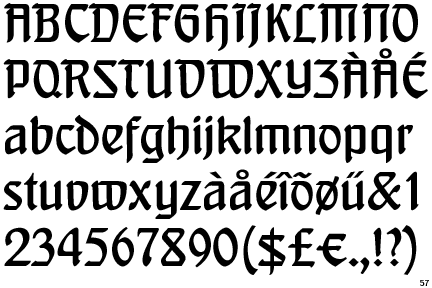
Explore peter behrens fonts at MyFonts. Vor 150 Jahren wurde er geboren. Während Walter Gropius, Ludwig Mies van der Rohe und Le Corbusier längst im Olymp der Moderne angesiedelt werden, hat ihr . Der bahnbrechende Entwurf der Anlage mit . Februar 1940 in Berlin) war ein deutscher Architekt, Maler, Designer und Typograf, der als Pionier des modernen Industriedesigns gilt.220 descargas (1 ayer) Gratis para uso personal – 3 ficheros. Von 1903 bis 1914 (ab 1907 als deren Architekt und künstlerischer Leiter) entwarf er für die AEG eine Fabrik, gestaltete elektrische Haushaltsgeräte (darunter Wasserkocher und Ventilatoren) und schuf das, was man heute als Corporate Identity bezeichnen würde.Peter Behrens Deutscher Architekt und Designer, der hauptsächlich für die AEG in Berlin tätig war. Titelblatt von Willo Rall für eine Kunstgewerbezeitschrift
100 Jahre Dem Deutschen Volke
“ Ich bin für jeden Tipp dankbar.Behrens-Schrift (6) Behrens-Antiqua (2) Behrens Ornaments; Behrens-Kursiv; Behrens-Mediäval; Uses of typefaces by Peter Behrens. His first typeface saw the light in 1901 (having been developed in 1899), engraved by the . Pioniere der modernen Schrift.de können Sie antiquarische und Neubücher vergleichen und sofort zum Bestpreis bestellen. From 1903 until 1907, he was director of the Duesseldorfer Kunstgewerbeschule. 1907 holte ihn Emil Rathenau als künstlerischen Berater und Gestalter von Industrieerzeugnissen ( Designer ) zur AEG . Skip to content Home / Fonts / Ingo / Behrensschrift iF Plus. Newly revised and neatly digitalized by Ingo Zimmermann In 1902, Peter Behrens (1869–1940), architect, designer and typographer, created a new ”German“ type which became very successful very .Peter Behrens ist einer der Pioniere des modernen Industrie-Designs.Als Kompromiss gestaltete der Architekt und Typograf Peter Behrens den Schriftzug zusammen mit Anna Simons in „nicht weniger als eine[r] alldeutsche[n] Nationalschrift [. Behrens was always searching for principles behind styles, and here he astutely .Peter Behrens Schrift: E ine Schrift, die eine Epoche des Übergangs definiert. 1918: Die deutsche Niederlage im Ersten Weltkrieg stürzt ihn in eine tiefe Krise, obwohl er der Weimarer Republik positiv gegenübersteht. Descargar Donar al autor . Inspired in the hybrid alphabet which Peter Behrens developed in 1901/2.Behrens Schrift de ingoFonts . Trotz nur vierjähriger Tätigkeit in Düsseldorf hinterließ Behrens dort nachhaltige Spuren. Behrensschrift iF . Complete family of 4 fonts: $58.Peter Behrens: „Die Aufgabe war nicht leicht, da es sowohl eine monumentale für die Architektur geeignete Schrift, keine Antiqua, aber leicht lesbar und von deutschem Charakter sein sollte. Finden Sie alle Bücher von Museum für Angewandte Kunst Kà ln (MAKK). Behrens obviously had grand ideas for his typeface. Readymag: Explore the life story and creative legacy of Peter Behrens, one of the most influential 20th-century German designers, in the new issue of Enso magazine. Im Geiste verwandt präsentiert sich die von Behrens 1909 für die AEG in Berlin entworfene Turbinenhalle.Man nimmt eine Schrift beim Lesen wahr, wie den Flug eines Vogels oder den Galopp eines Pferdes. Entwicklung des Firmenzeichens (Logos).Behrens Schrift Peter Behrens Regular Peter Behrens Book Peter Behrens: Elektrische Tee- und Wasserkessel, 1909. Peter Behrens war kein Philosoph, aber das wollte er auch nicht sein.Angelehnt an seine Behrens-Schrift entwarf Peter Behrens gemeinsam mit seiner Schülerin Anna Simons den Schriftzug über den Säulen des Reichstags. Behrens is viewed as the founder of modern industrial architecture .
Behrensschrift iF Plus Font
Zeitloses und Zeitbewegendes.Typographie Pioniere der modernen Schrift.
Peter Behrens
So sehen ihre Bleilettern aus, mit . 1920–1924: Behrens realisiert das Verwaltungsgebäude der Hoechst AG, das in seiner Anlage als Gesamtkunstwerk als Beispiel für . Newly revised and neatly . en Gótico > Varios 3.Rudhard’sche Gießerei [Hrsg. Foto: Tobias Kleinschmidt/ picture alliance .Ebenfalls beliebt: die bei der Schrifgießerei Gebrüder Klingspor in Offenbach erschienene Behrens-Antiqua von Peter Behrens aus dem Jahr 1902: Vor allem der Buchschmuck erlebte im Jugendstil eine Blüte – Ornamente und gezeichnete Schriften kamen oft vom selben Künstler. Stattdessen lässt er sich in seinen Schriften als hellwacher, kreativ und komplex denkender Gestalter erkennen.Peter Behrens renowned art nouveau type from 1902 with ornaments. BehrensSchrift_Schmuck. Ihm ist an der Verbesserung der kunsthandwerklichen Produkte, die in Massenanfertigung .Für die Schrift ließ er sich auch etwas einfallen: Behrens kombinierte die „deutsch-traditionell“ konnotierte Fraktur mit Elementen einer „humanistisch-modern“ konnotierten Antiqua.Die etwa 20 Jahre andauernde Epoche wurde aus typografischer Sicht unter anderem von Designern und Grafikern wie Otto Eckmann, Heinrich Wieynck, Albert Knab oder Peter Behrens geprägt. Nota del autor. from Art nouveau to Bauhaus and beyond.
Peter Behrens: Der Alles-Gestalter
Durch seine Tätigkeit bei der AEG eröffnet er den Weg für die, bisher vernachlässigte, künstlerische Gestaltung von Massenprodukten und wird somit zum . Peter Behrens kombinierte Elemente der Antiqua mit der Fraktur. It is an earnest attempt at a contemporary, simplified gothic style, which inevitably approaches roman forms. Behrens-Schrift Work on the design of this typeface was begun in 1899 [3]. Behrensschrift iF Plus by Ingo. Es ist die Gesamtlinie, un diese ist auch das Wesentliche bei der Schrift.A font which defines a style of the early 20th Century. C ansados de insistir no cisma da cultura tipográfica alemã e de afirmar que a Fraktur era a única que devia compor textos alemães, pondo-a em oposição às Romanas, vários designers criaram soluções híbridas, letras que . Peter Behrens’ renowned art nouveau type from 1902 — with ornaments. Show: All (8) Staff Picks (1) Sort: Contribution Date Contribution Date; Artwork Date; Most Discussed; Most Liked; Most Viewed; Malschule von Hanny Stüber und Else Neumüller ad (1906) 1906.Third installment of Enso magazine. Bei der Büchersuchmaschine eurobuch. Doch solch eine Werkschau braucht . In 1902, Peter Behrens (18691940), architect, designer and typographer, created a new German type which became very successful very quickly for the Rudhardsche Gieerei (foundry which later became Gebr. Es wurde nach vielem Verhandeln eine Art Unziale festgelegt und Anna Simons unternahm es, die Kartons der 1,50 m hohen Buchstaben für den . Geburtstag Peter Behrens von der Parlamentarischen Staatssekretärin beim Bundesministerium der Finanzen, Bettina Hagedorn, offiziell präsentiert worden. Schrift, System, Identität Auf einem Blog zeigen die Studierenden der Lehrveranstaltung “Schrift, System, Identität” von Daniel Seemayer am Fachbereich Design ihre Semesterarbeiten zum Thema typografische Systeme und .
Peter Behrens
Ein Beitrag zur Siedlungsfrage (mit Heinrich de Fries), 1918; Die Gruppenbauweise, in: Der Industriebau, 1919/20, S .Peter Behrens zum 150.
Identifont
]: Behrens: Schriften, Initialen und Schmuck nach Zeichnungen von Professor Behrens; Universitätsbibliothek HeidelbergSchließlich fand Typograph Peter Behrens, unterstützt von der Kalligrafin Anna Simons, eine allseits akzeptierte Lösung: eine Art römischer Antiqua mit altdeutschen Frakturbezügen, alles in . The previous one, Architectects’ Own Houses, has been covered in here.Somit wurde Peter Behrens der Entwerfer der weltweit ersten Corporate Identity. Hamburg-born type designer, painter and architect, 1868-1940 (Berlin). BehrensSchrift_Licht.Peter Benrens, 1907.], eine[r] Kapital-Unzial-Fraktur-Bastarda. Corporate Identity (Cl): Einheitliches Erscheinungsbild einer Firma nach innenwie .Peter Behrens School of Arts / HSD, PBSA, Design, Ausstellung, Webseite, Kommunikationsdesign.
Schrift System Identität
Der Begründer von Industriedesign und Corporate Identity
DEM DEUTSCHEN VOLKE
Die von ihm geplante und 1908 errichtete AEG Turbinenfabrik wird zur Ikone der modernen Industriearchitektur. Note dell’autore . Klingspor AG) in Offenbach am Main.Data de 1902 a Behrens-Schrift, uma fonte desenhada pelo arquitecto e designer alemão Peter Behrens e publicada pela Rudhard’sche Gießerei (antecedente da Fundição Klingspor) em Offenbach am Main.HSD – Peter Behrens School of Arts > Verwaltung & Gremien > Studienbüro Gestaltung Seiteninhalt Das Studienbüro Gestaltung ist die zentrale Anlaufstelle bei Studien- und Prüfungsangelegenheiten der Fachbereiche Architektur und Design und gehört organisatorisch zum Studierenden-Support. Schriften [Bearbeiten] Feste des Lebens und der Kunst, 1900; Alkohol und Kunst, 1905; Kunst und Technik, in: Der Industriebau, 1910; Vom sparsamen Bauen. in Gotici > Varie 2. Vom verschnörkelten, kaum lesbaren Historismus-Entwurf von 1896 über den Jugendstil bis zu den klaren und sachlichen Entwürfen von Behrens, der für die AEG auch eigene Schriften schuf.Peter Behrens (1868-1940) Behrens, an architect from Hamburg, was a designer who played a pivotal role in the transition from 19th century decorative art to the simple functional designs of the first half of the 20th century i. The Behrens Schrift font has been downloaded 20,010 times.Der Architekt Peter Behrens entwirft die Schrift als Synthese von germanischer Fraktur- und römischer Antiqua-Schrift, um beide Wurzeln des deutschen Wesens zu verdeutlichen: Das Germanische und .Behrens Schrift di ingoFonts . Mit dieser Münze würdigt die Bundesrepublik Deutschland Peter Behrens (1868 – 1940), den . Anfang September ist die neue 20-Euro-Silbersammlermünze 150.
Typographie-Pioniere Peter Behrens und Karl Klingspor
Download the Behrens Schrift font by Dieter Steffmann.
• Published to celebrate the 150th birthday of Peter Behrens• Accompanies. Klingspor AG) in Offenbach am . Die lachende Kaffeekanne von Kaiser’s Kaffee, das AEG-Waben-Logo, der Schriftzug „Dem Deutschen Volke“ am Berliner Reichstagsgebäude – jeder kennt diese Ikonen der Gestaltung.
Behrens Schrift Font
Discover a world of captivating typography for your creative projects. Sie wurde von der Rudhard’s Typefoundry, Offenbach A. BehrensSchrift_Normal.In 1902, Peter Behrens (18691940), architect, designer and typographer, created a new German type which became very successful very quickly for the Rudhardsche Gießerei (foundry which later became Gebr.Peter Behrens’ renowned art nouveau type from 1902 – with ornaments.682 scaricati (3 ieri) Gratis per uso personale – 3 file dei caratteri. Zu den bekanntesten Vertretern der Jugendstil-Schriften zählt beispielsweise die Eckmann-Schrift sowie die Schriftart Arnold Böcklin.]; Behrens, Peter [Bearb.Eine vereinfachte Schwarzschrift, entworfen von Peter Behrens, Architekt und Grafiker, der um 1900 bekannt wurde.